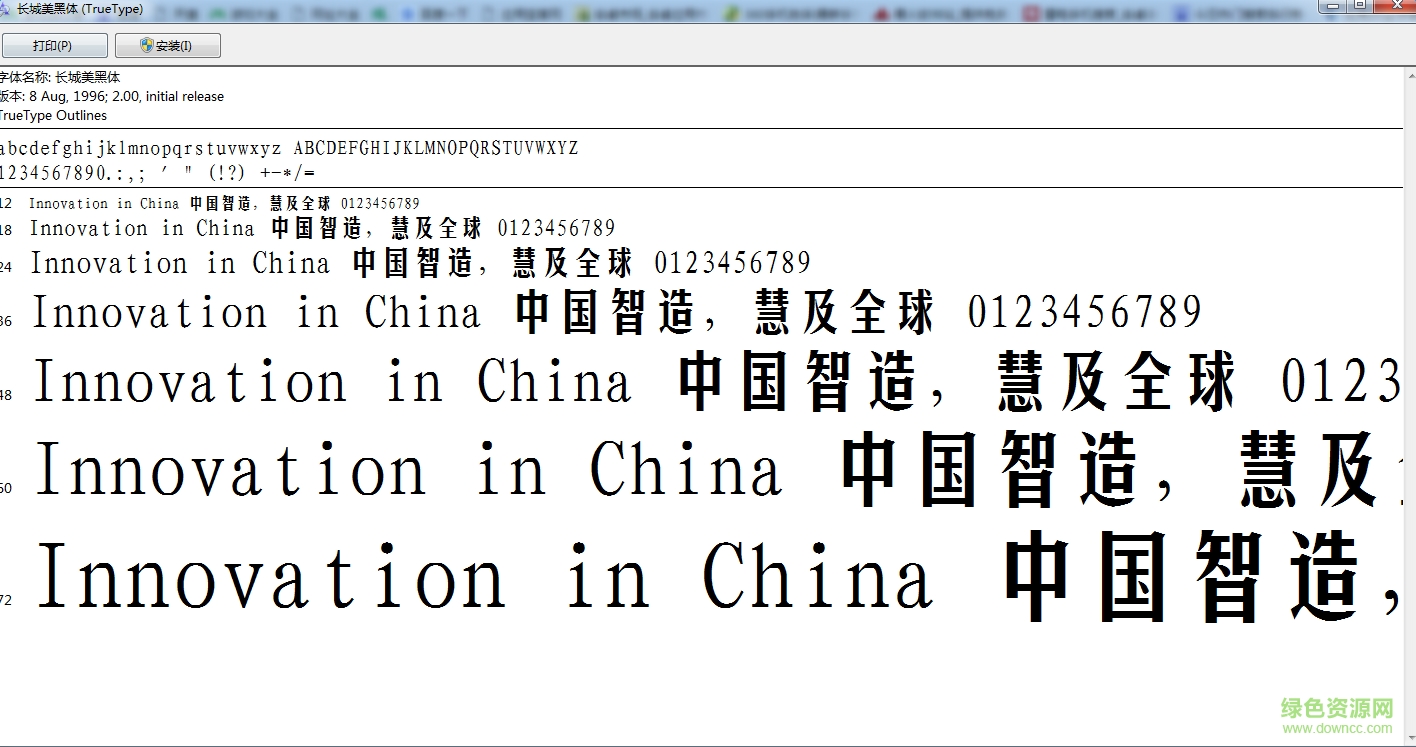
gmhe00m是什么字體?gmhe00m字體又叫長城美黑體,是一款符合字體構(gòu)形規(guī)律的黑體字體,該字體骨絡(luò)分明,清秀工整,實用性強,喜歡的小伙伴快來綠色資源網(wǎng)下載吧!
1.中國的字體設(shè)計是在印刷術(shù)的產(chǎn)生和發(fā)展中應(yīng)運而生的。在古代,中國的字體設(shè)計曾有過輝煌的歷史時期,在宋朝時進入黃金時代。
2.清朝末年,鉛字排版印刷術(shù)傳入中國,字體設(shè)計進入鉛字時代。這個時期的字體設(shè)計既要帶有傳統(tǒng)文化的審美慣性,又要符合鉛字印刷的工藝要求,字體設(shè)計走到了轉(zhuǎn)折的關(guān)口。
3.鉛字印刷是印刷走入機械化、工業(yè)化時代的標志,但在這一時代里,印刷字體設(shè)計卻始終無法超越手工勞動的制約,無法擺脫刻模、鑄字、撿字、排版等一系列印前繁雜工藝的束縛